一篇文让你秒懂版式规划
大家好,今天的课程题目是“让你秒懂版式规划”。很多刚刚入行的小伙伴,在一开始接手文案到有想法着手去,经常会有困惑,客户或者文案给的乱糟糟的文字,怎么把它处理成一个良好的具有传播属性的画面呢?这也是今天课程想要去解决的问题。本篇教程分为以下几个部分,首先是如何快速的整理文案,其次,确立信息的优先级,然后,我会详细的介绍几种常用的版面划分方式,这也是本节课的重点,最后再给大家分享一下作图之前,绘制手稿的思路。好的,话不多说,开始我们今天的课程吧。
提到整理文案,不知道小伙伴们有没有联想到,现在特别火的整理收纳术。估计有强迫症的同学看到整理后的图片,会非常舒服。
它同样是要求整理人拥有一个划分区域,归类物品和注意物与物之间距离的能力,是不是和我们整理文案很相似呢?
很多时候我们接手的文案,都是零碎甚至复杂的,这个时候就需要我们在开始设计之前,先整理信息。
我们可以看看日本著名的设计师,佐藤可士和,他是如何利用整理术来处理信息的。
很多小伙伴,是不是在一拿到文案后就直接开始设计呢?
前期准备阶段,在我们一接手客户或文案给的文字资料时,我们对这个资料的认知是模糊的,有时候只是大体知道方向或行业是什么,这个时候就需要我们运用整理术,先来整理好文案。
信息整理完毕后,原来模模糊糊的文案,现在变得清晰可见,但是它们仍然是一个没有逻辑顺序的状态。
这个时候我们就要把相关联的信息整理组合到一起去。
信息已经全部都按照关联性分好组了,我们就开始一组一组进行整理,这个时候就需要我们设定好整理的优先级。在这里从一号三角形开始整理。
好的,现在每组信息里面的层级,我们也都划分的清晰明了了。
到了这一步我们,再仔细的了解一下文案,这几个组之间的关系是什么,在这里我们看到三角形加圆形等于正方形,也就是说这里面正方形组的信息是最重要的。
所以我们在开始做图的时候,就要把正方形组的信息放置在版面最显眼的位置,这样最有利于信息的传播。
通过上面的演示,我们学习到了,在正式开始设计之前,需要有前期准备信息阶段,信息整理完毕后观察信息,列出有效信息,设定整理的优先级,理清因果关系,找出本质,这6个步骤,来逐步的整理信息,这个过程也是设计师逐步明白客户需求和设计思路的过程。好的,那接下来通过案例部分,手把手教大家整理文案信息。
大多数情况下文案信息是不完整的,这个时候就需要我们自己进行一定的头脑风暴,去寻找和补全信息,就是把模糊的信息逐渐变得清晰的过程。
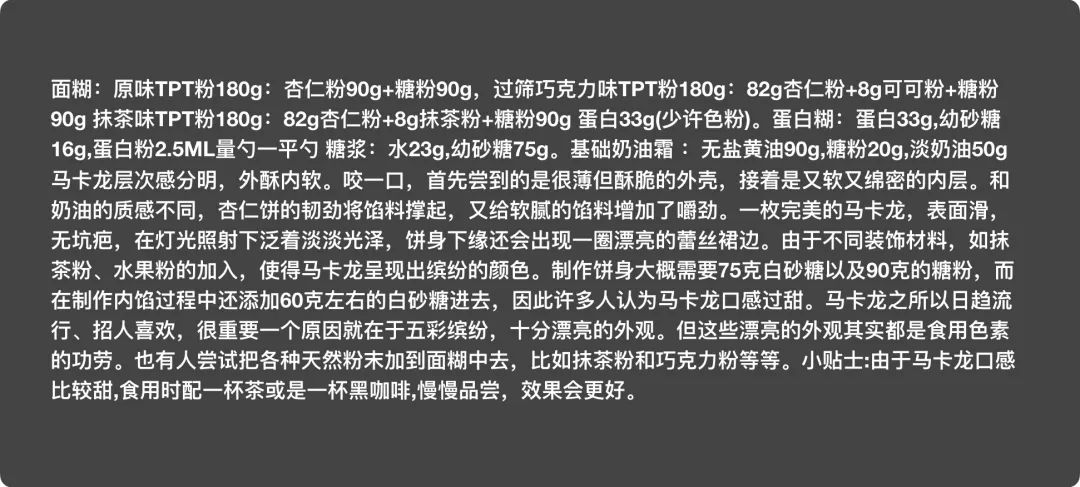
在我们把信息补充整理完毕以后,我们开始分析信息,把信息划分成一个一个小组。
在这里我们看到,高亮的文字很明显是配料表,我们把它与其他信息区分开。
这一部分的高亮信息,是甜品的介绍,我们同样把它与其他信息区分开。
这里由于有提示,我们也能很快的区分出来,这个应该是属于注释的那个部分。
在这里我们把整理好的信息,分别拿出来标上符号,按照之前讲的顺序来进行整理。
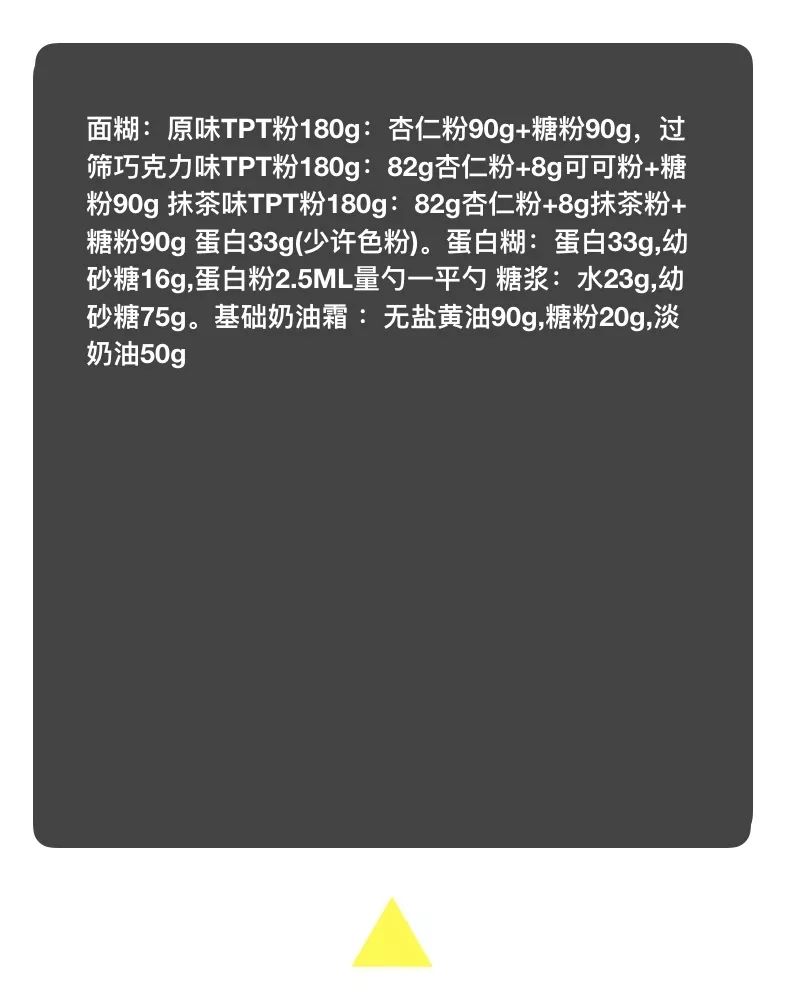
现在来看一下第一组的文案,从文案中可以知道,这个关于甜点的配料表的信息。
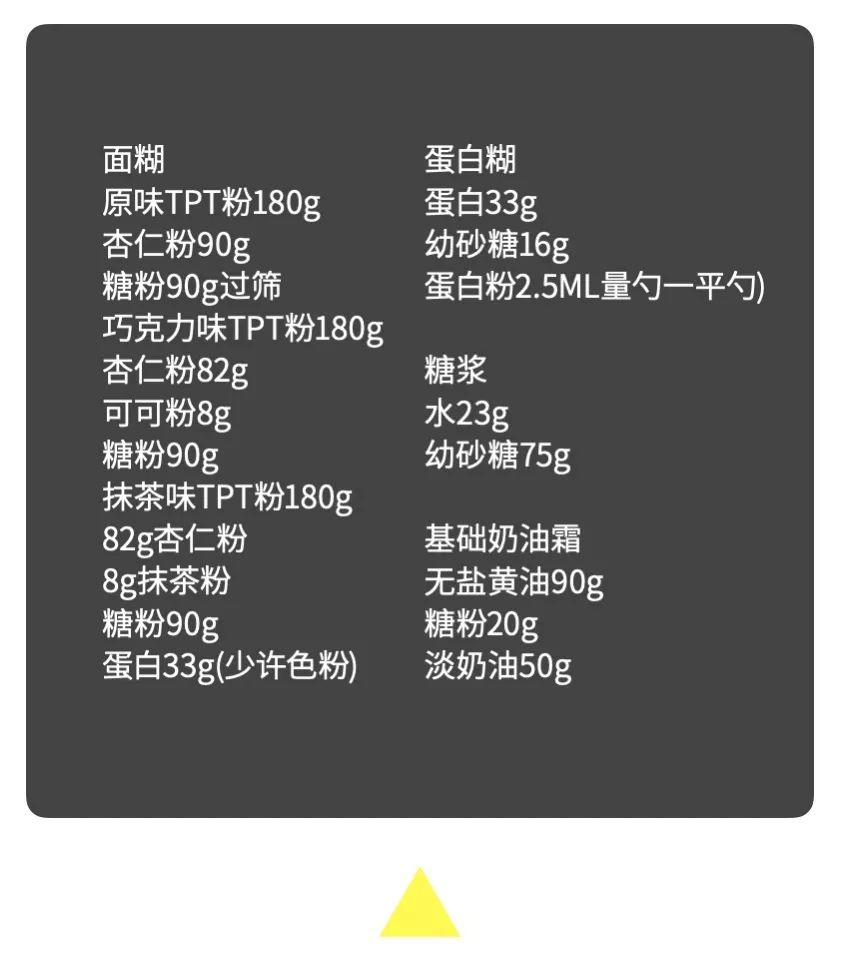
整理完成后,大幅度的提升了信息的识别度。
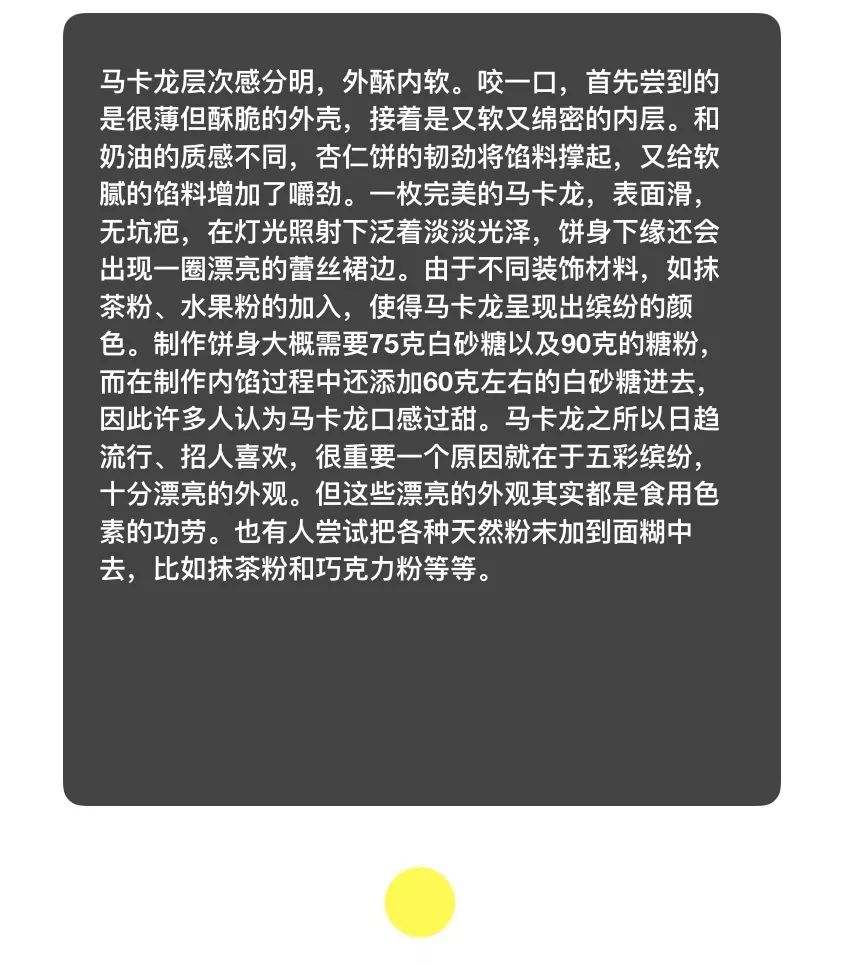
我们再来看第二组,这是一整段关于甜品的介绍,一整段文字阅读起来,会产生一定的阅读困难,这里我们将文字断行。
信息整理完毕后,大大降低了阅读的障碍。
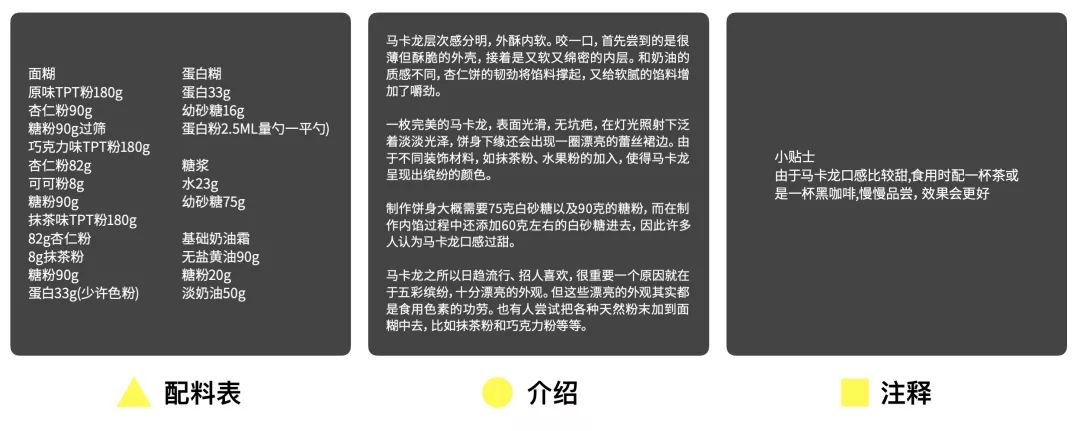
当三组的文案全部整理完毕后,我们就很清楚的知道,这三组文案分别想要传达的内容了。它们分别是:配料表,介绍和注释。
这里就需要我们理清它们三个的因果关系。我已经把所有可能的组合都列出来了,首先去掉以注释为主的信息组合。
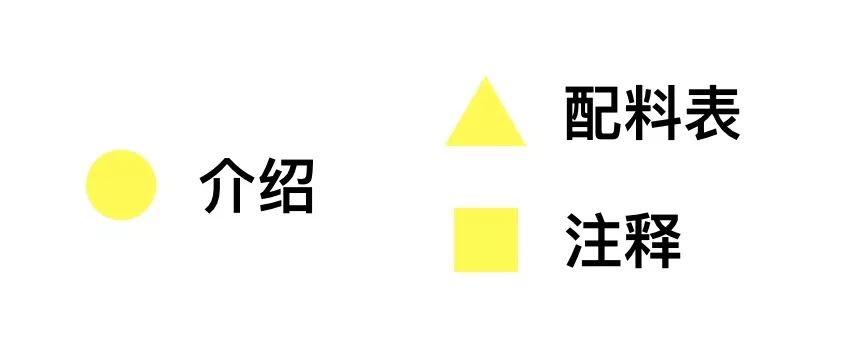
现在,我们已经理清楚因果关系了,也就顺理成章的推理出来了它们的本质。
在这里我给大家提供两个信息整理的思路,第一个就是“将杂乱的文字信息重新组合”。
我们还是以刚才整理好的配料表为例,现在的文字依然存在辨识度的问题,作为设计师,就要求尽可能的提高辨识度,这就需要继续整理这个文案。
我们将名称与重量重新组合,不同种类的信息进行成组区分,提升整体文字的识别度。
第二个信息整理思路是将文本的关键信息提炼出来。
我们再一次观察这个甜点的介绍文案,发现这个文案可以分成四个部分,口感描述、外观描述、制作成分、流行趋势。在这里我们在外观描述中提炼出一段文字,作为这段话的摘要部分。
这样在阅读这段信息的时候,就可以更加容易的理解整段文字的内容了。
按照上面的步骤,一步一步整理,整个过程也加深了我们对文案的理解,那么既然已经明确了,一个文案中的重要信息是什么,下一步需要做的就是如何把这些信息传达出来,这也就进入了我们今天的第二部分的内容了,如何确立优先级。
通过上面的学习可以准确的找到重要信息了,现在需要做的就是确立这些信息的优先级别。
这里有四个一样的苹果,我们并不能从画面知道哪个苹果是最重要的。我们把这个苹果放大,立刻就可以知道它优先级别是最高的。
这个道理同样适用在文字组上,单纯看这段文字,我们并不知道哪一句话是重点内容。
我们按照同样的方式,把最重要的信息放大,就可以知道它们的优先级别。
这里有三台无人机,同样发现不了哪一个是最重要的。但是我们只需要改变这个无人机的位置,就可以知道它们的优先级别。
调整位置的思路,重新来修改文案,达到明确优先级别的目的。
在这里有三个在举重的人,同样都分不出来他们的优先级别。去过健身房的同学,应该深有体会,在健身房你能举起的重量越大,越能吸引别人的目光。现在给中间的人,举铁的强度加倍,是不是优先级别立刻就显现出来了!
我们继续以这段文字为例,可以是通过改变颜色或者增加字重,来改变文字的强度,
通过上面的学习,我们知道了可以通过调整信息的大小,位置和强度来确定信息的优先级别,这个不仅仅只适用于文字信息,同样适用于图片信息,这样在规划版面的时候,就可以按照信息的重要程度合理的放置信息了。根据版面中的信息的多少,版面划分的方式分为:二分法、三分法和四分法,通常来说重要的信息在版面中所占的面积和比例也是最大的,次要信息以此类推,所占面积依次减少,但并不是绝对的,这个同学们要明白。那么接下来,我们了解一些常用的版面划分的方式。
首先我们来看一下二分法的几种形式。
在这张海报中,主视觉采用字叠图的方式作为主体,置于画面下方,占最大的面积和比例,其余文字放在上方,这就是典型的二分法画面。
接下来,我们来看一下三分法,这里的信息层级也就进一步丰富起来。
这个画面中主视觉占版面最大面积,主要信息和次要信息也会一目了然。
这个画面同理,主视觉占据画面最大面积,主要信息和次要信息,虽然面积占比区分不大,但是通过文字的大小对比,有效的确立了信息的优先级别。
在海报中三分法也是很常见的方式。
三分法,不仅仅只是横向的划分版面,同样可以横竖结合划分版面,我们继续来看几种常见的划分方式。
在这个画面中,最重要是餐厅的展示图片,主标题次之。
这个版面中,这四张图片传递的信息基本一致,但是将其中的一张图片放大,占居版面的最大面积,就确立了明确的优先级。
我们来看一下四分法的常用划分方式。
设计师在开始正式的工作之前,还可以利用绘制手稿的形式来缩短思考设计的时间,锻炼我们的画面布局的能力,提升工作效率。下面给大家分享一下,绘制手稿的方法。
首先可以将图片简化为线框。
将文字简化为线段,内文文字用细线表示,标题等文字用粗线表示。